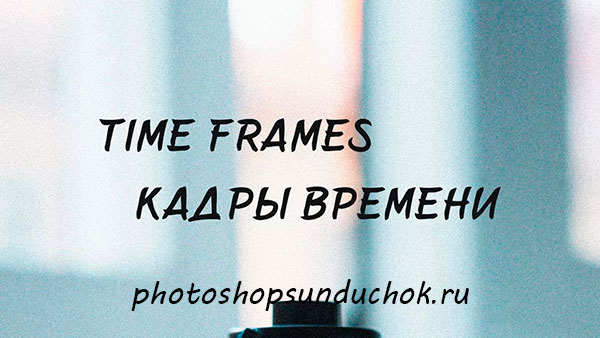
Шрифт Belepotan
Шрифт Belepotan – это мягкий и гладкий рукописный шрифт кисть.
Шрифт имеет два вида начертания: regular и italic, а так же содержит заглавные буквы, цифры и символы.
Шрифт отлично подойдет промышленного дизайна, брендинга, оформление соц. сетей и т. д..
Поддерживает латиницу и кириллицу.